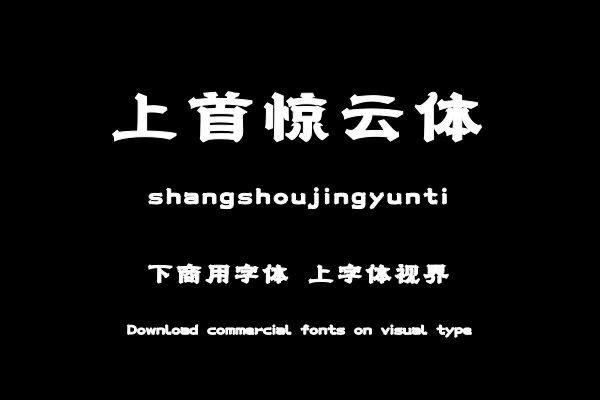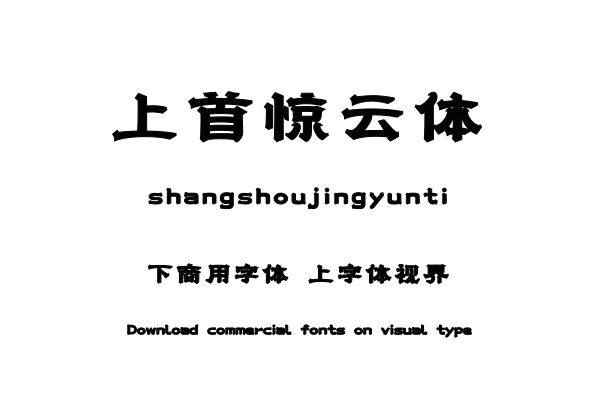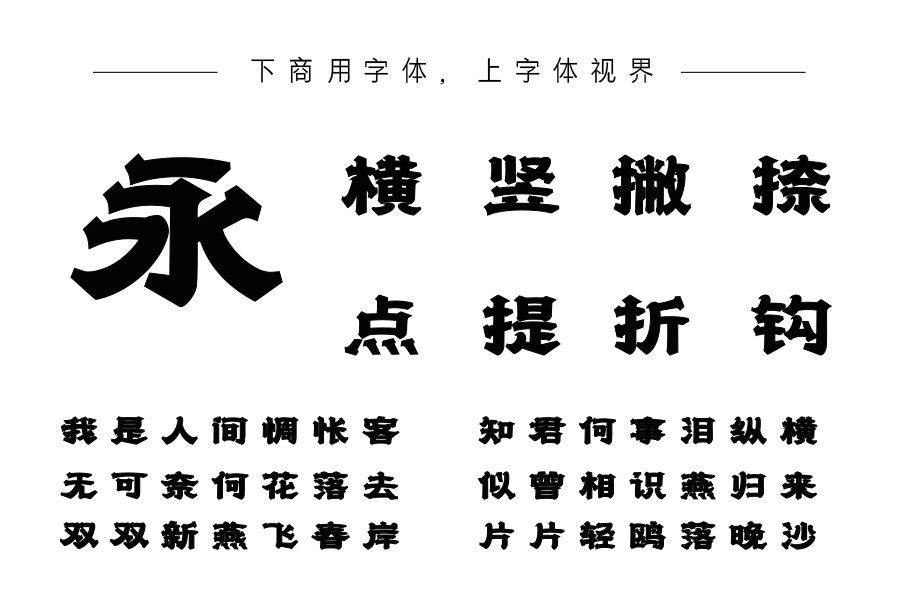
上首惊云体,此套字体以不规整的笔画做出较为典雅的感觉,赋有力量感。微微拱起的笔画给予字体骨骼感和精神气,气势恢弘。像参天大树一样生机盎然,蓬勃生辉。购买须知:“下载服务费”与“字体VIP”所获得字体 仅用于个人非商用, 商用请联系付费授权。本字体为电脑用字,手机没有root权限不支持直接手机换字(手机如何root,请自行百度搜索教程)。购买前请先 了解清楚后再付款 ,字体为虚拟产品无法回收 一旦购买不支持退款。